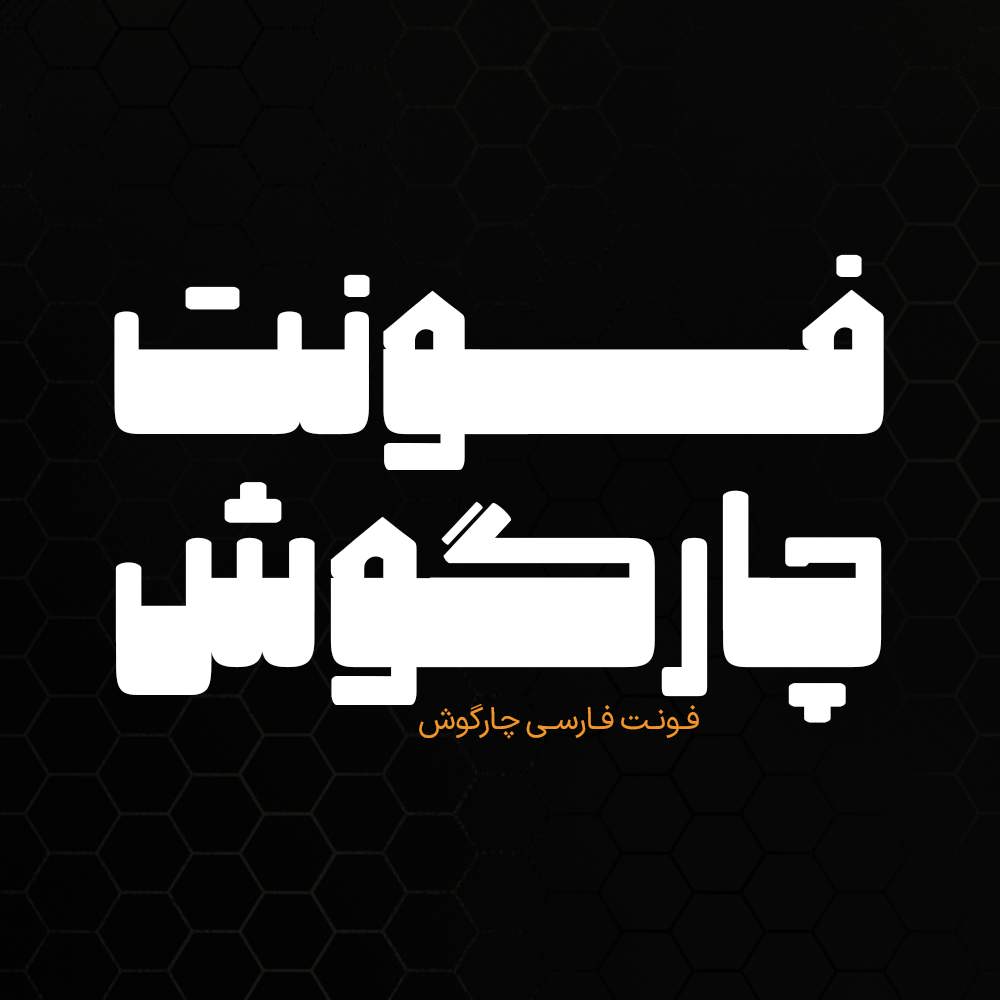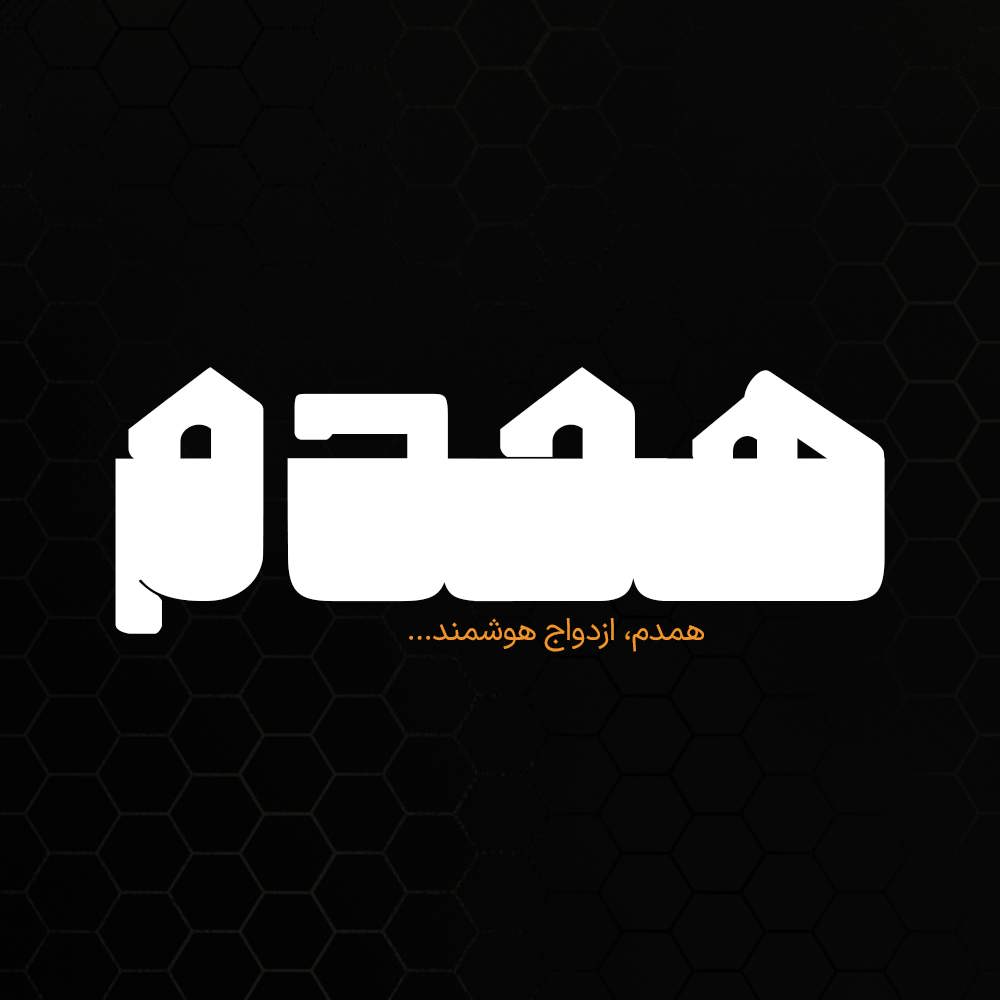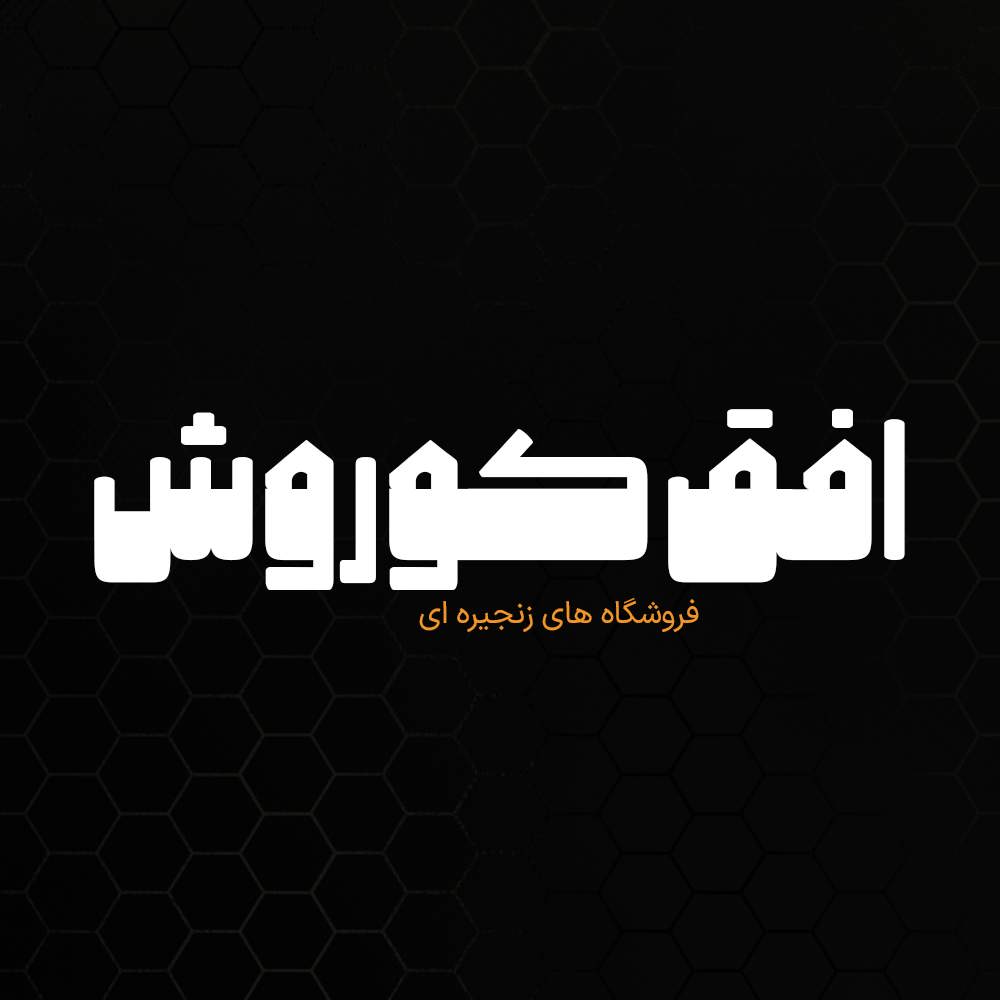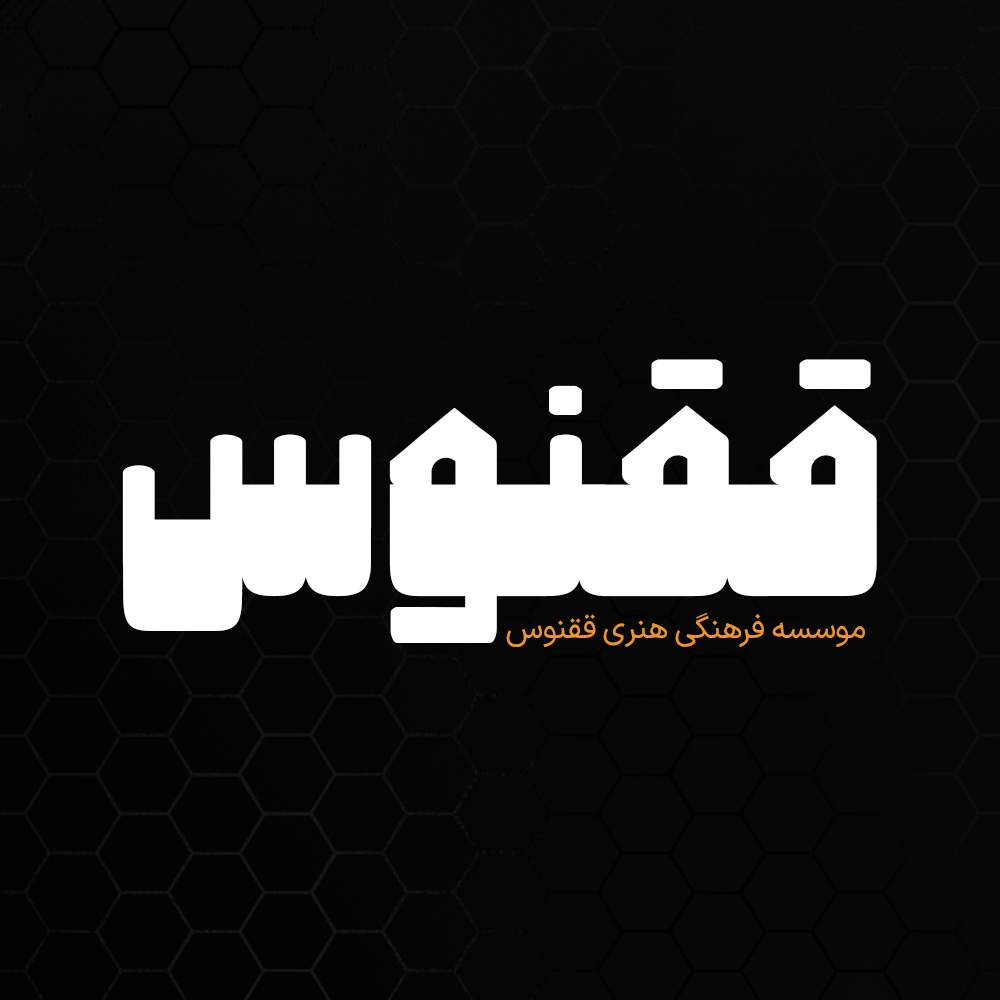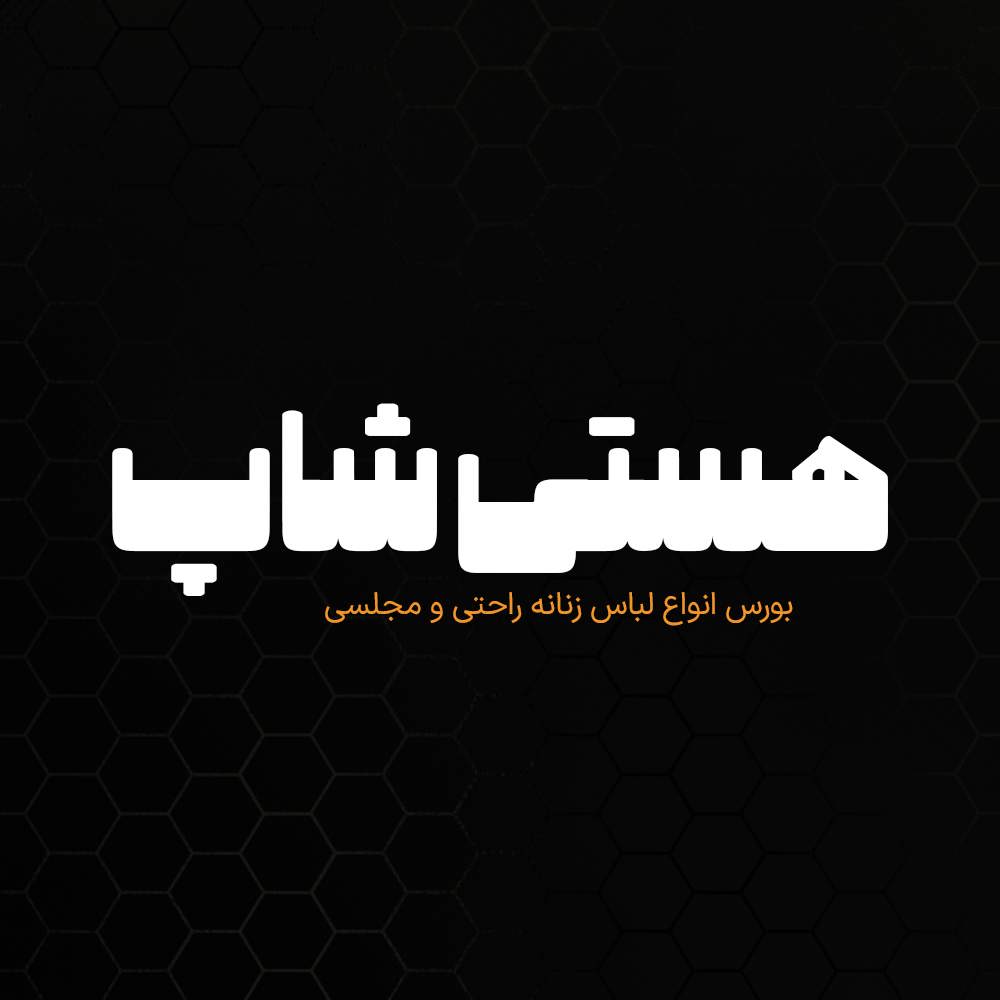
فونت فارسی چارگوش از دسته فونتهای فوق سنگین با بدنه قطور است. این سبک طراحی در حروفنگاریهای دهه ۴۰ و ۵۰ مرسوم بوده و فونتهای متعددی نیز در سالهای اخیر به این سبک ساخته شده است. تفاوت اصلی فونت فارسی چارگوش با دیگر فونتهای این دسته، هندسه ساده و کنتراست ضخامت حروف است. فونت چارگوش به سادگی در نرم افزارهای تحت ویندوز از جمله مجموعه برنامه های فتوشاپ، کورل، آفیس، اینشات و… قابل اجرا میباشد. طراحان وب سایت و گرافیست های خلاق می توانند از این فونت زیبا فونت در طراحی پروژههای تبلیغاتی و تجاری خود کمک بگیرند. فونت فارسی چارگوش یک فونت تک وزن با کاربرد طراحی لوگوتایپ و طراحیهای مختلف همچون کتاب و تولید محتوای متنهای کوتاه و عناوین میباشد. از آنجایی که فونتهای عربی فاقد حروف “گچ پژ” هستند و مشکلاتی در تایپ حروف “ک” و “ی” دارند در فونت چارگوش حروف “گچ پژ” و همچنین اعداد فارسی و انگلیسی اضافه شده است و نقطه های فونت و حروف “آ، ق، ک، ل، ن، ی و…” بازطراحی شده اند تا بتوانید تمامی متن فارسی را به وسیله این فونت تایپ کنید. در ادامه برای شما نمونه تایپ های این محصول حرفه ای رو آماده کردیم که میتونید مشاهده کنید.
پیشنمایش و نمونه تایپ های فونت چارگوش